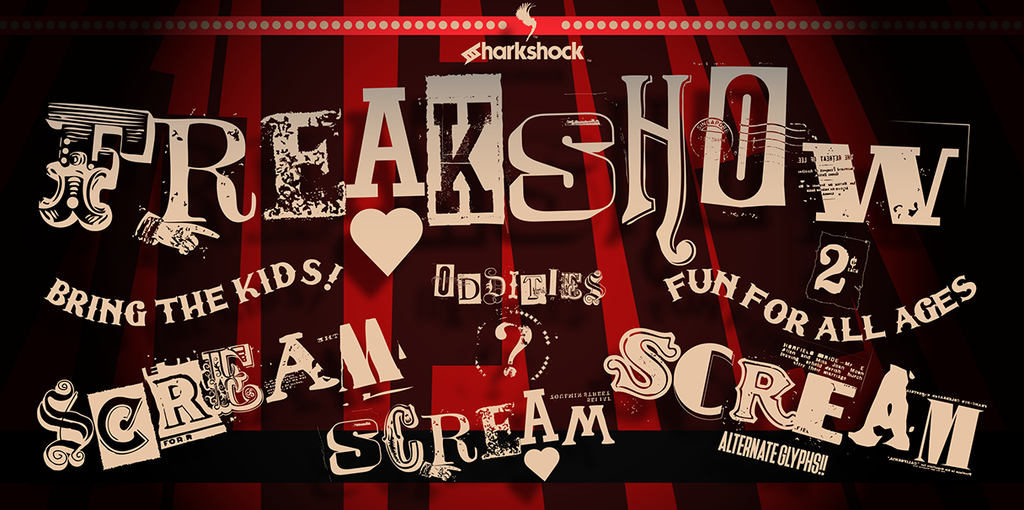
A Freakshow Font é uma elegante escolha para designers que buscam uma mistura única entre letras robustas e detalhes arredondados. Criada pelo designer Hamilton no ano de 2016, essa fonte Gothic apresenta um visual moderno e contagiante. Com sua estrutura angular e seus detalhes chamativos, Freakshow pode ser usada com sucesso para criar uma atmosfera sinistra ou inusitada em designs diversos como logotipos, publicidade e até mesmo letras de música. Com seu arquivo OTF (OpenType) e TTF (TrueType), Freakshow oferece flexibilidade tanto em programas digitais quanto impressão. Suas características revelam a habilidade do designer Hamilton em criar um estilo que se destaca no universo dos fonts, especialmente entre o público amante de fonts góticas. Esta font é perfeita para quem busca trazer uma atmosfera diferente e moderna aos seus projetos gráficos. Com sua design sofisticado e detalhes inusitados, Freakshow pode ser usada com sucesso em qualquer tipo de aplicação visual, seja para criar um efeito chamativo em sua marca ou simplesmente dar vida à sua criatividade no design de letras.